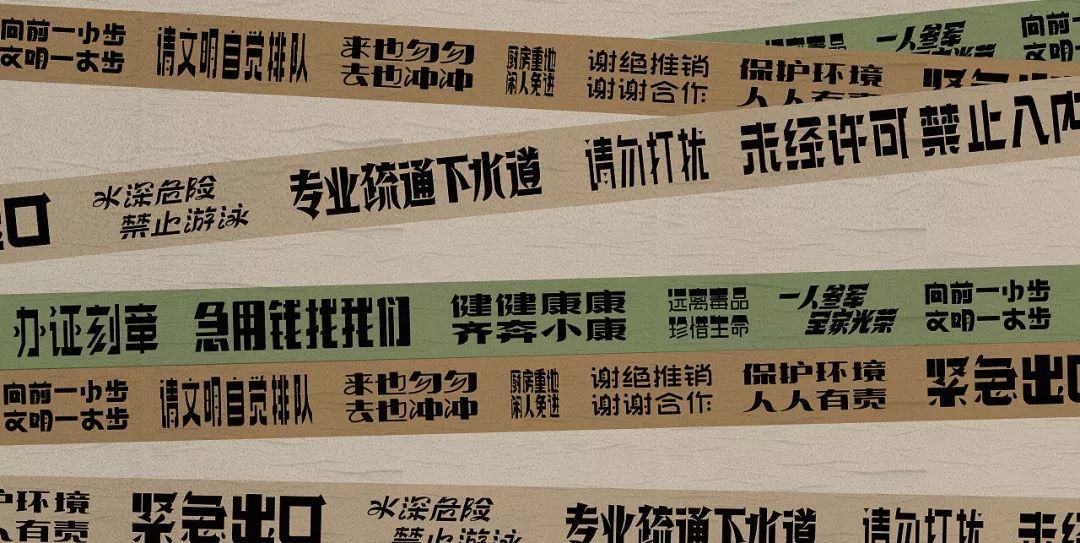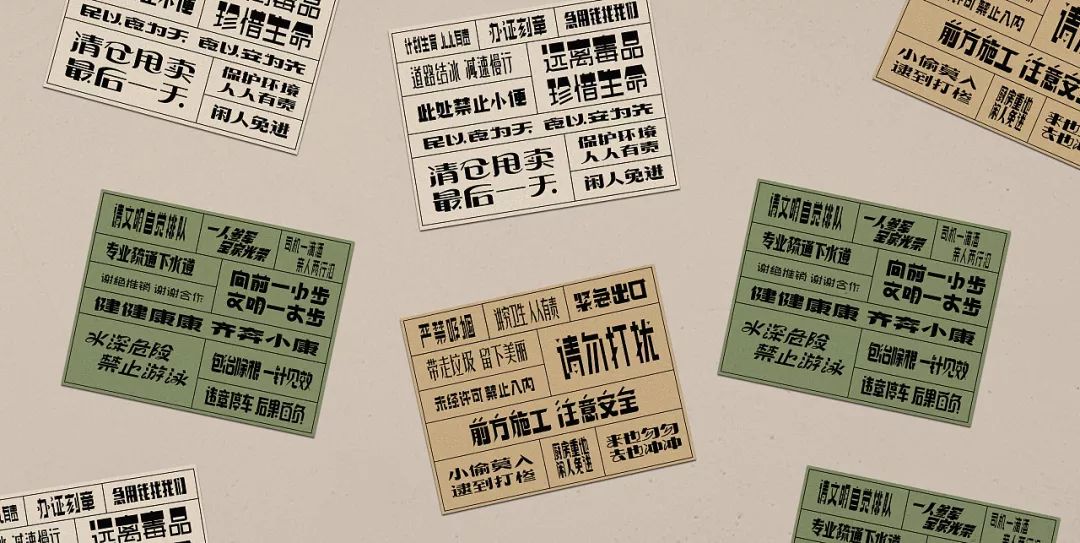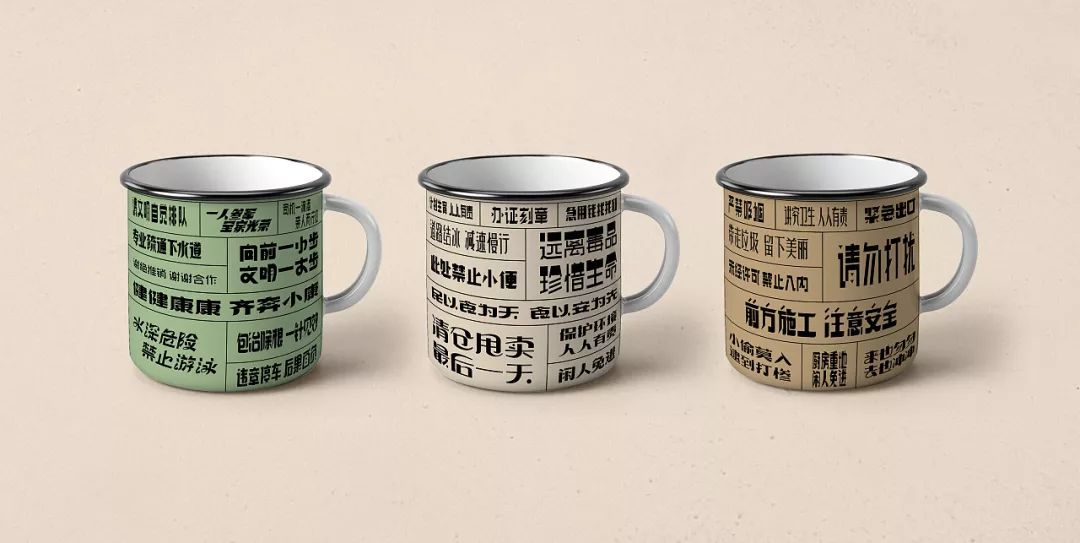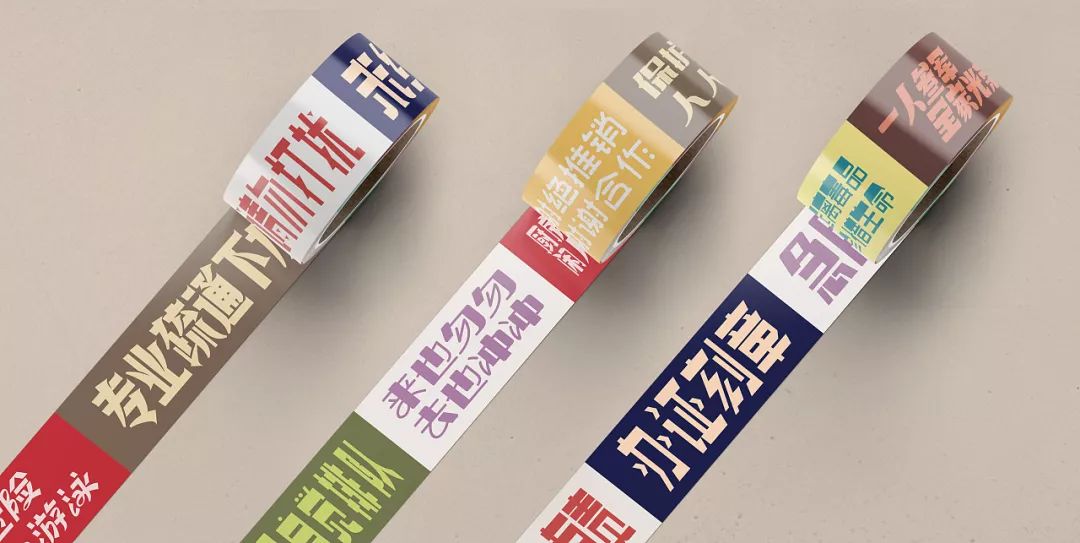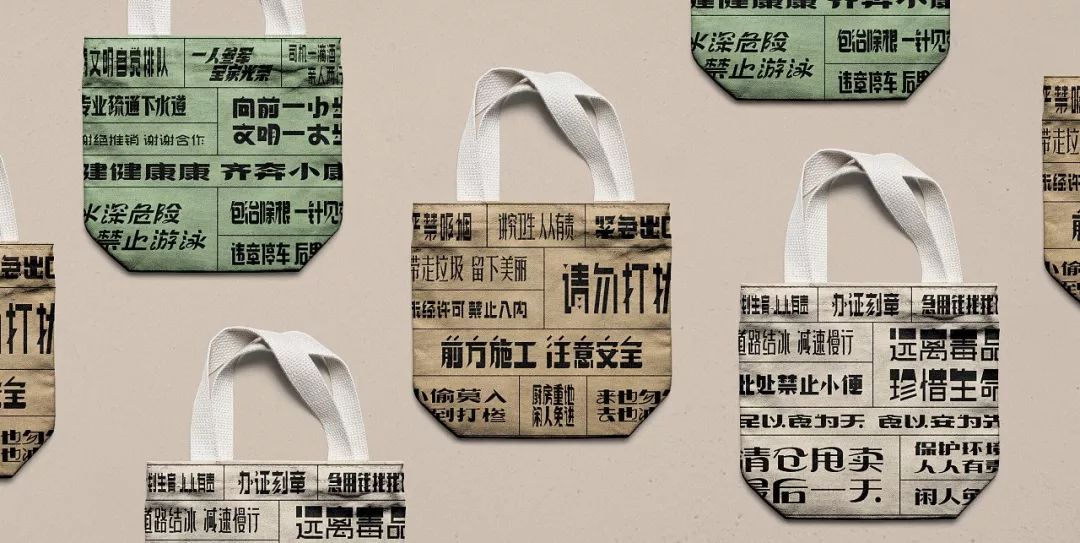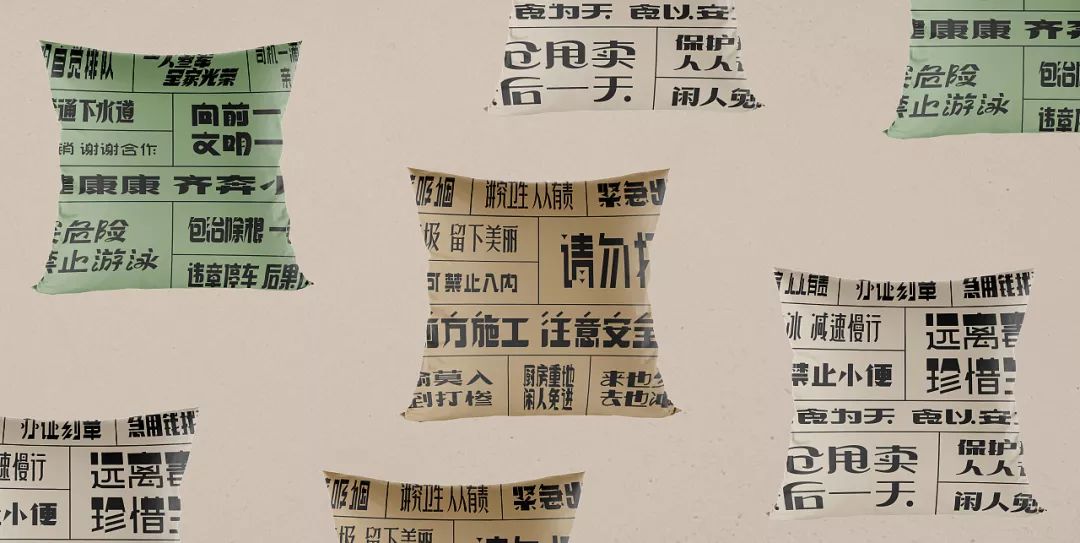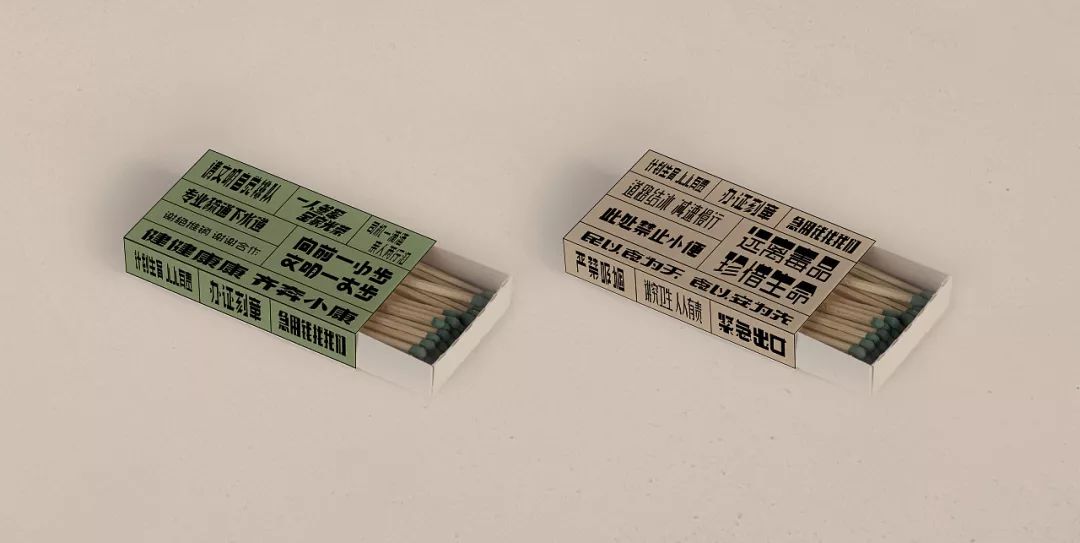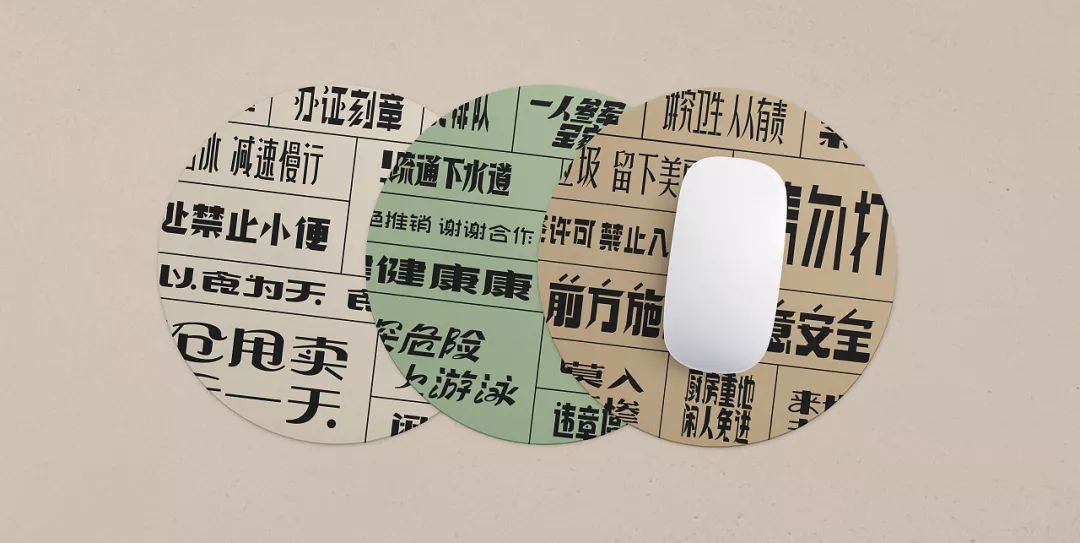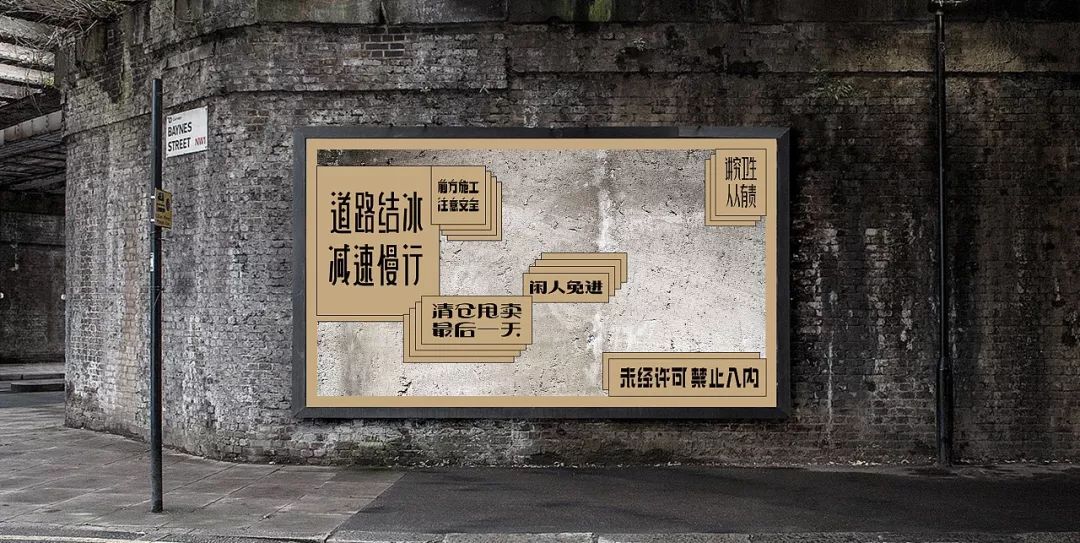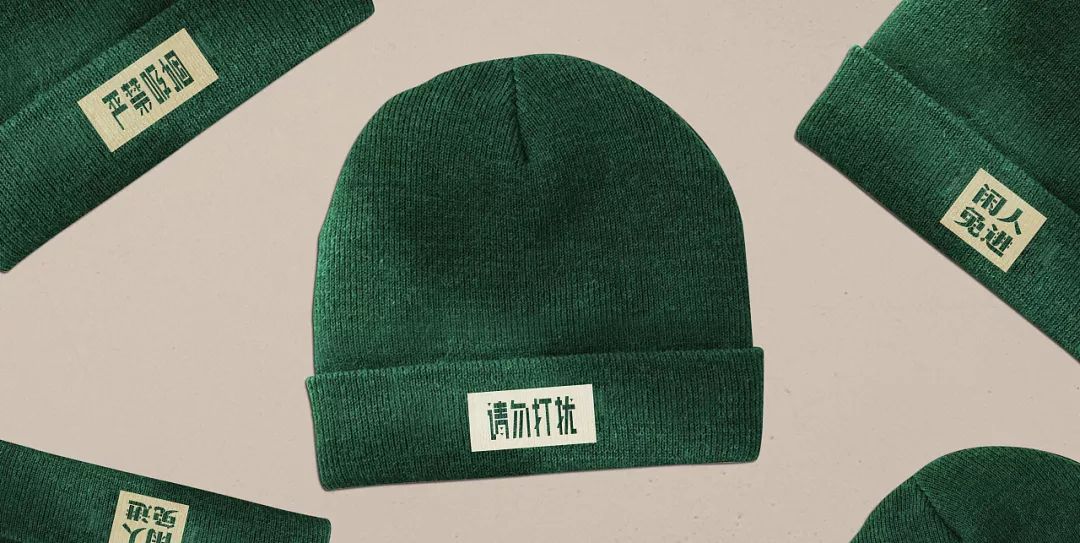
那些城市的牛皮藓,居然被玩出了花!
故事的起因是这样的:那天去卫生间,看到了极为熟悉的两行字:向前一小步,文明一大步。
于是乎,灵感乍现了,手都没洗,我就赶紧跑回到工作室,跟小伙伴们解释了这个想法,大家的普遍反馈是,这个创意,还是挺有“尿性”的……
我们日常生活中,每天都会看到很多标语,在马路上,在小区里,在墙面上……有的标语很正经,有的则很调侃,如果用字体设计的方式来表达,每个人估计都会有不同的方式和创意,而这次,我们选择了老字体的风格,每一句口号,每一款字形,形式各异,特点鲜明,但无一例外,他们都保留了一种的穿越的、复古的感觉。
大概列出了五六十句这样的标语,然后从中筛选了相对靠谱的30组,经过一周多时间,大家完整的设计了出来,并做出了十几张不同的应用效果,还选择了其中6组,做出了动态展示。
好了,上面听完兵克的BB之后,开始听我的BB了!
中间这个杯子,此处禁止小便,我是拒绝的!!
这个环保袋拿出去,我觉得还是很时尚的!
火柴现在已经没有及个人用了。但是不要骗我,侧面是黑色的。。。
做抱枕,也是可以的。感觉很个性。
这个手机壳可以考虑量产,我有兴趣!
这个帽子颜色太环保了,不适合中国人!~
看一波动态图,也是很过瘾!
好久没有看过这么有想法的作品了。
大家看完这些老东西,是不是觉得自己还有很多东西可以学?!